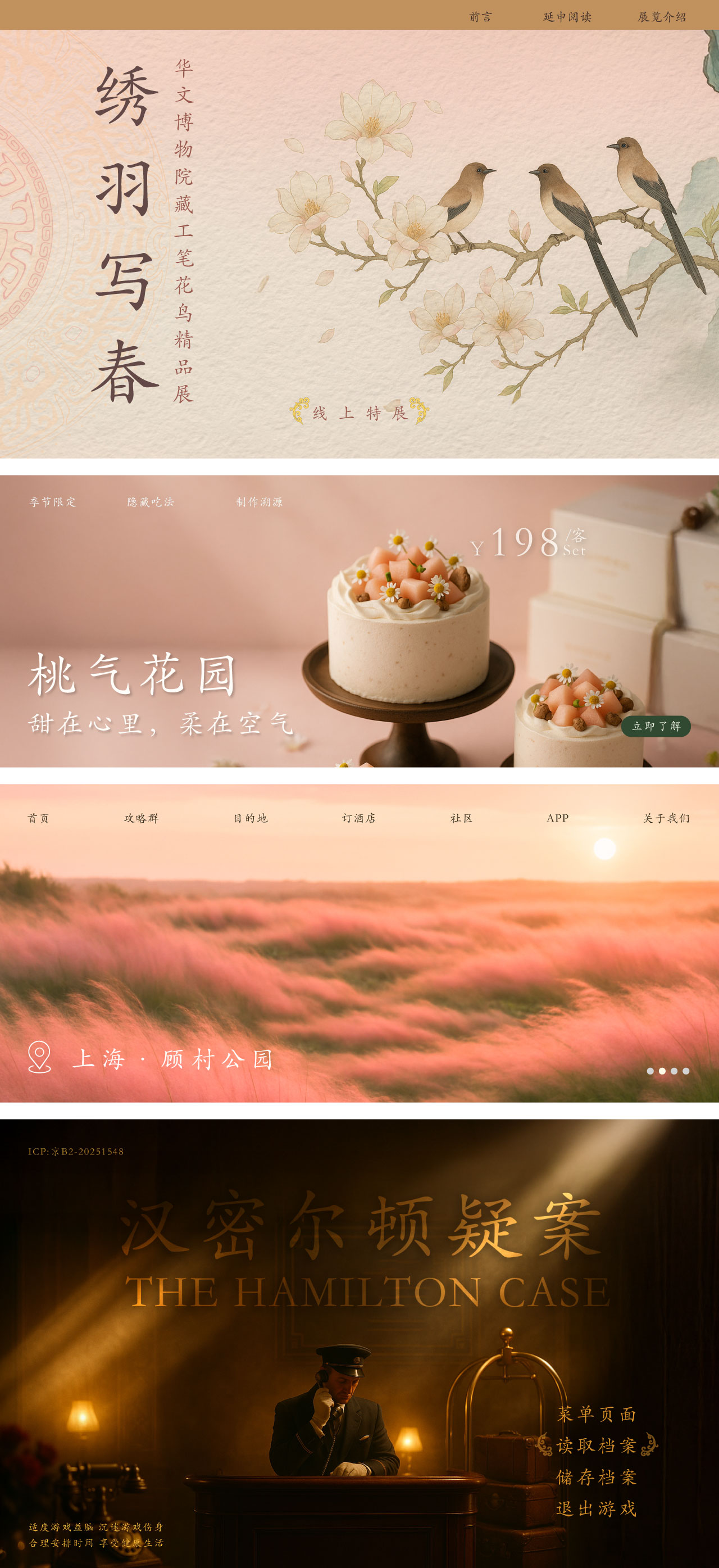
华文楷体 / STKaiti / Regular
华文楷体
华文粗楷 / STCukai
华文中楷 / STZhongkai
华文楷体 / STKaiti
常州华文
字体介绍:
华文楷体由毛笔书写的楷体演化而来,其基本笔形、笔画运笔规律与毛笔相近,字形朴实端正,笔法舒展有力,流畅自然,适用于屏幕显示、书报杂志和多种媒体信息的小标题及正文用字。